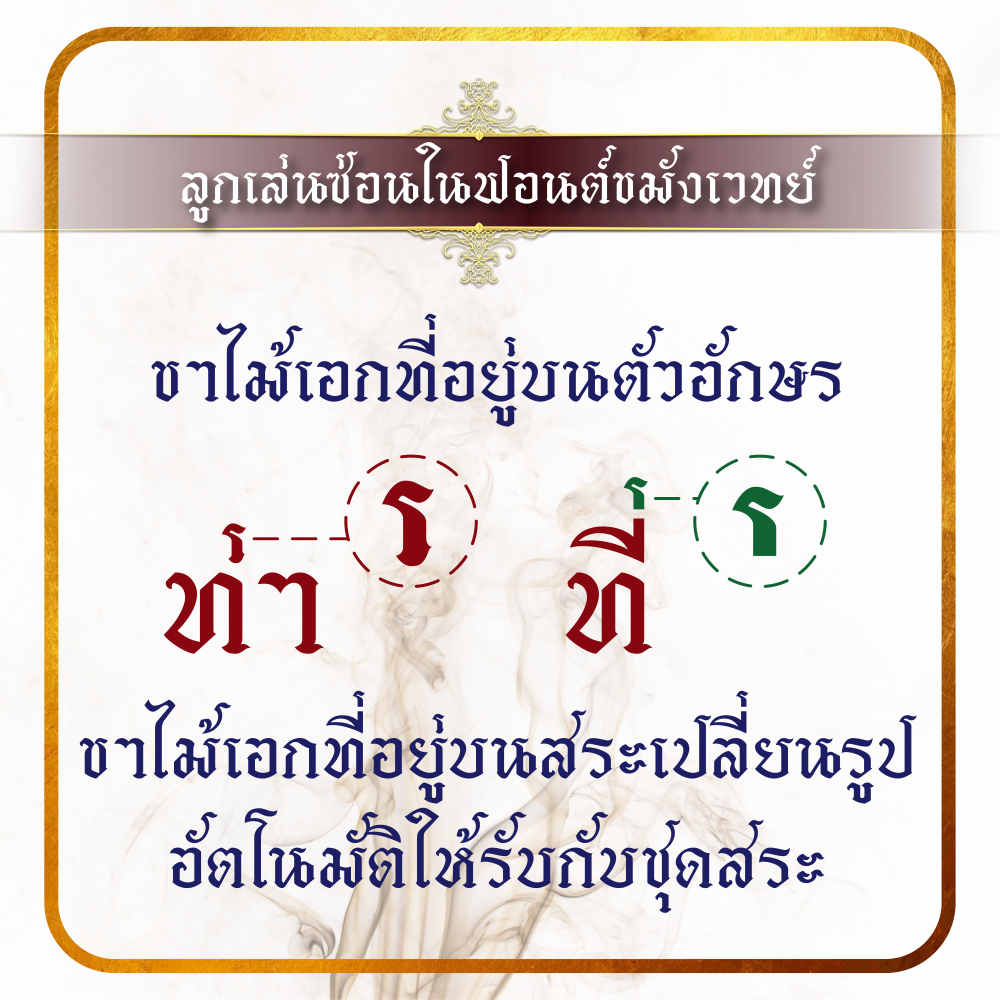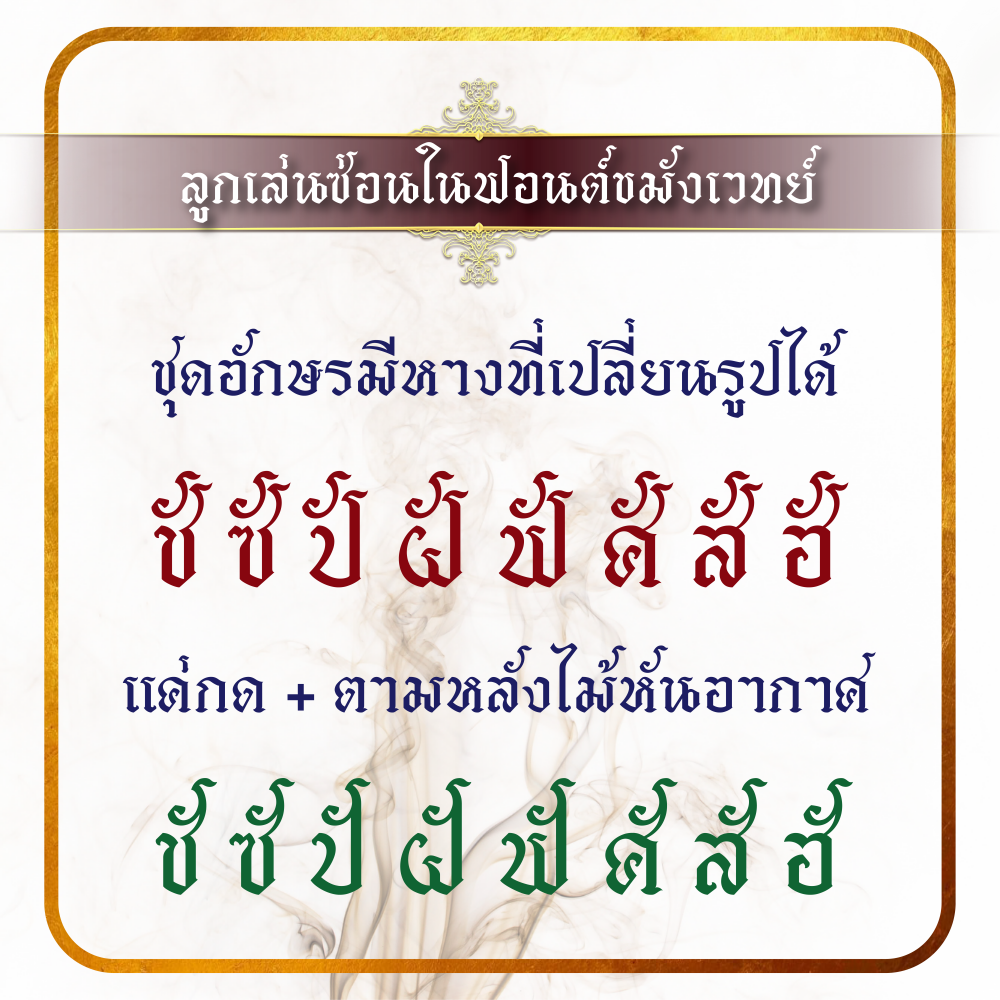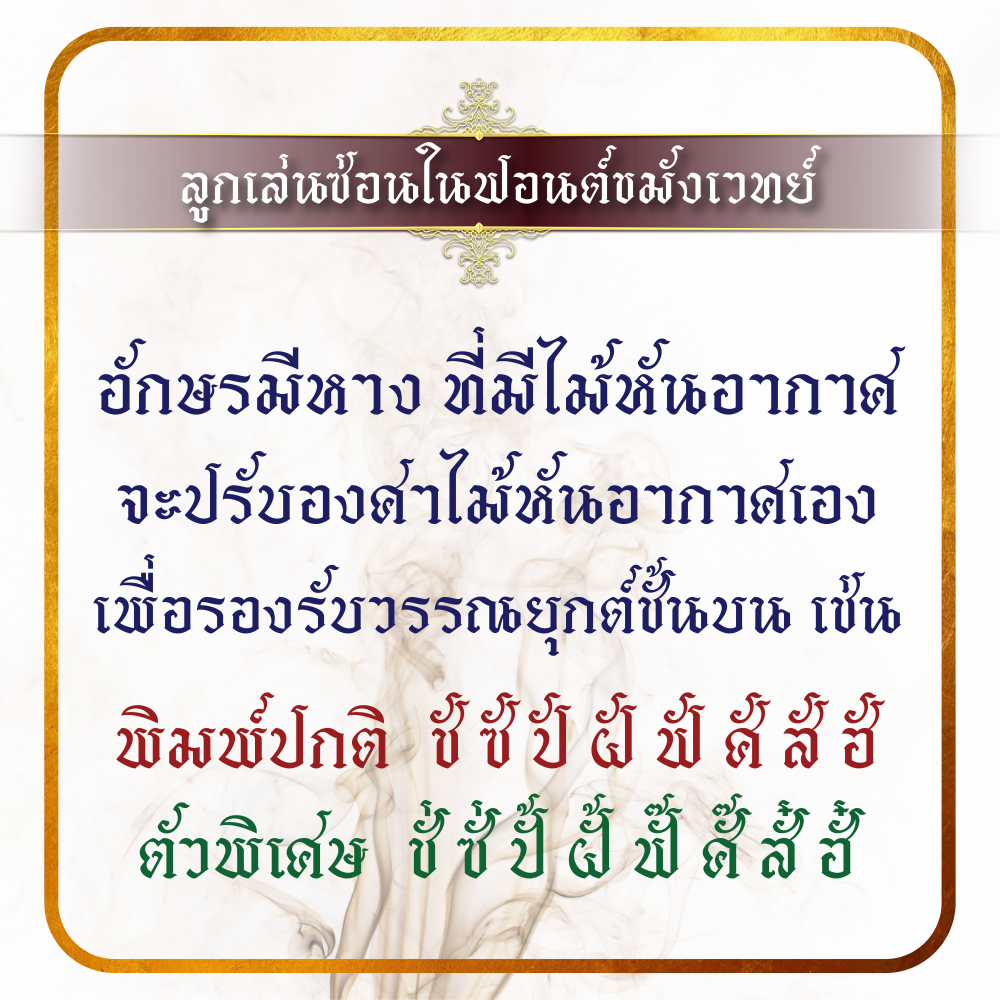
ขมังเวทย์ (j.devilfont@Khamang Wet)
ฟอนต์ ขมังเวทย์
ผลงานฟอนต์ที่ตัว 7
ชื่อฟอนต์ ขมังเวทย์  เป็นชุดอักษรไทยโบราณ
ชุดอักษรไทย-อังกฤษ
ปรับแก้เปลี่ยนอักษรชนกันแบบอัตโนมัติ ในหมวดภาษาอังกฤษ
อักษรไทยมีลูกเล่นสามารถหางรวมกับวรรณยุกต์ได้  ช ซ ป ฝ ฟ ศ ส ฮ
ชุดไม้หันอากาศปรับองศาเองให้รองรับวรรณยุกต์ชั้นบน
สระ อิ อี อึ อื ในชุด ป สามารถปรับสั้นได้ด้วยการกดเครื่องหมายลบ ( - ) ตามหลัง
รายละเอียด ฟอนต์ขมังเวทย์
- การใช้ kerning ในการจัดช่องไฟระหว่างตัวอักษร
- การใช้ mark เข้ามาจัดสระ วรรณยุกต์
- เพิ่มลูกเล่นที่ โ ใ ไ ที่ยืด-หด ความสูงในเวลาพิมพ์
- เจอวรรณยุกต์ชั้นบน เช่น ที่ไป ชี้ให้ ตี๋ให้ จะไม่เจอปัญหาทับกับ โ ใ ไ
- สระ อิ อี อึ อื ในชุด ป สามารถปรับสั้นได้ด้วยการกดเครื่องหมายลบ ( - ) ตามหลัง
- อักษรไทยมีลูกเล่นสามารถหางรวมกับวรรณยุกต์ได้  ช ซ ป ฝ ฟ ศ ส ฮ ด้วยการกดเครื่องหมายบวก ( + ) ตามหลัง